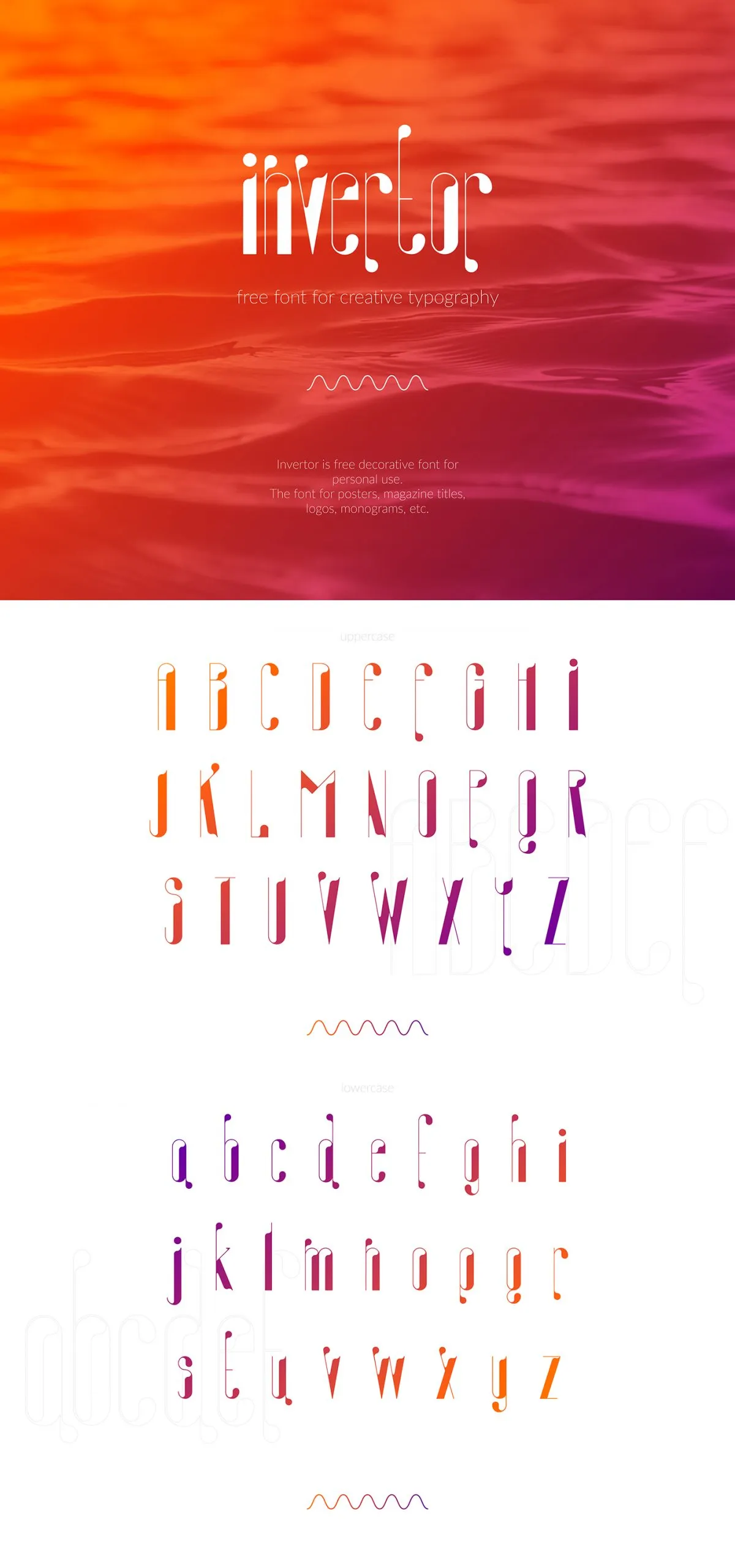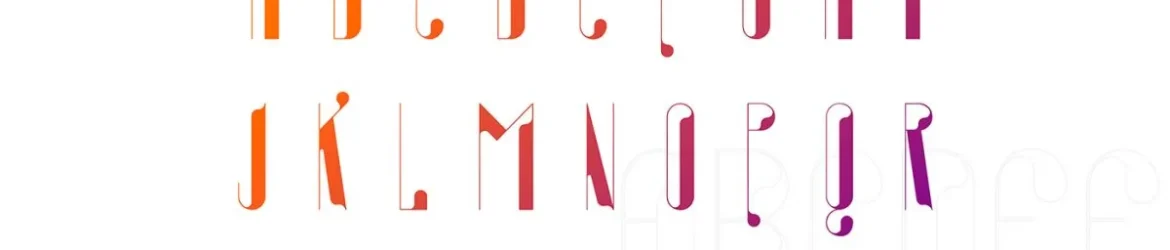
Invertor Font – Download Grátis
A Invertor é uma fonte desenhada pelo designer Hamilton para uso pessoal, mas acreditamos que vale a pena compartilhá-la com outros criadores de materiais impressos. Esta font foi desenvolvida para fins educacionais e treinamento, permitindo aos usuários entenderem melhor o processo de criação de fontes digitais. No entanto, percebemos que pode ser um desperdício não compartilhar esta font incrivelmente versátil, ideal tanto para aplicações gráficas em outdoors quanto para títulos de revistas e logos, além de usar-se em monogramas ou até mesmo nomes de empresas. Com certeza vale a pena explorar as possibilidades criativas desta fonte moderna e resistente à estilização, perfeita para projetos que exigem uma aparência única e dinâmica.